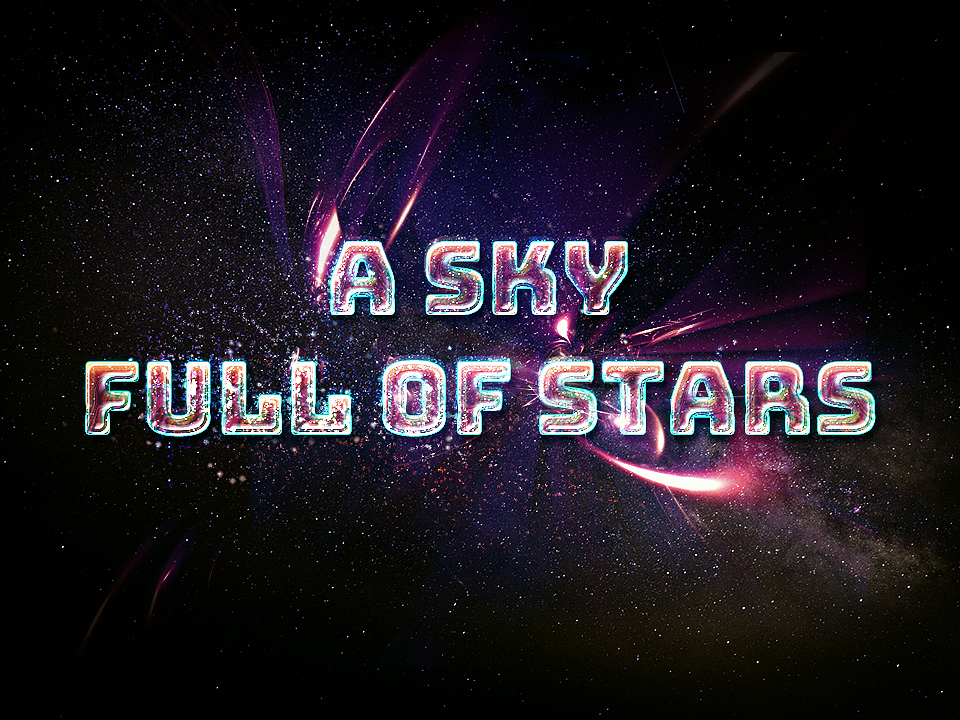
照猫画老虎29/30-星级文本效果与四星球
今天做的是星空文本效果,教程来源公众号阿门教你ps-虽然很费力,但是这效果!值了!极致炫彩星空字教程!by Ethan01,这种炫彩效果第一次做,主要是用不同类型的等高线进行制作,同时用不同效果的画笔进行描边,等高线真的很神奇!
这次的龙珠四星球是按昨天做的星空效果教程做的,然后为了显示出球体的效果把等高线的类型给换了,然后微调了颜色,最后就是加上高光就可以了。